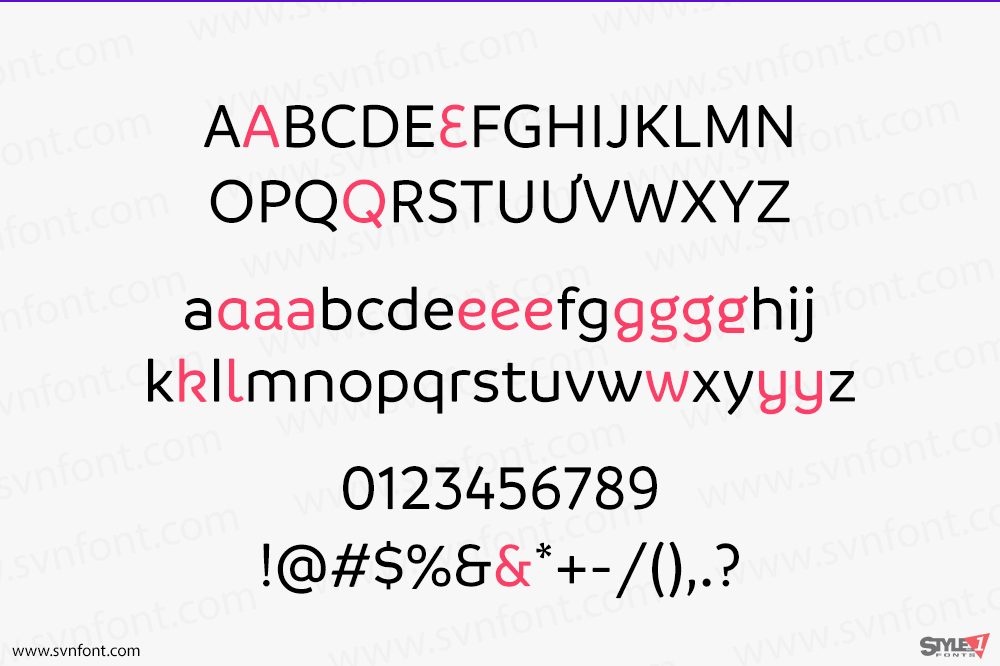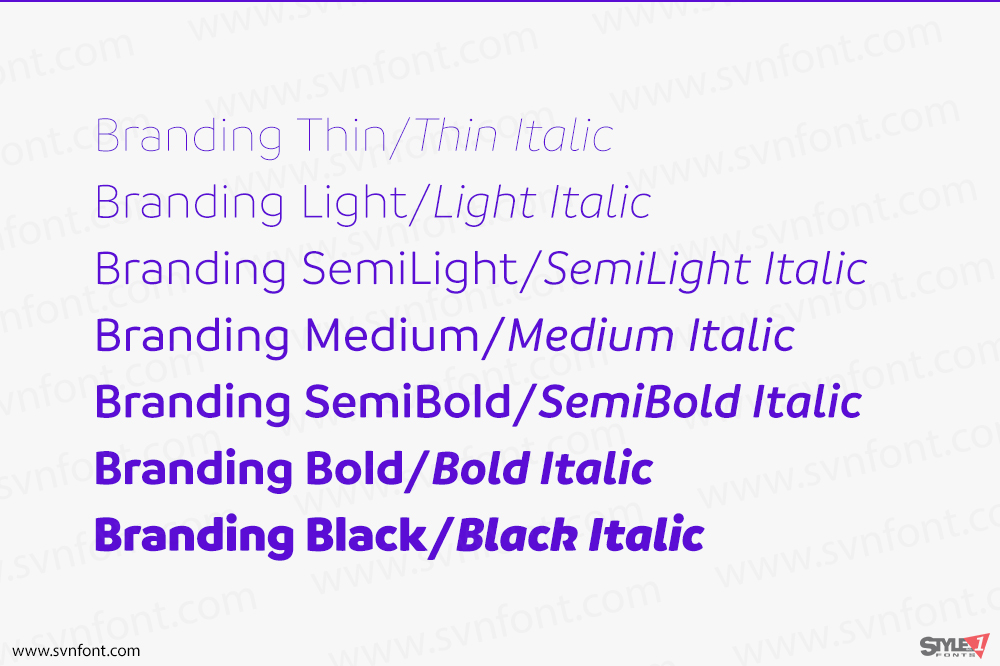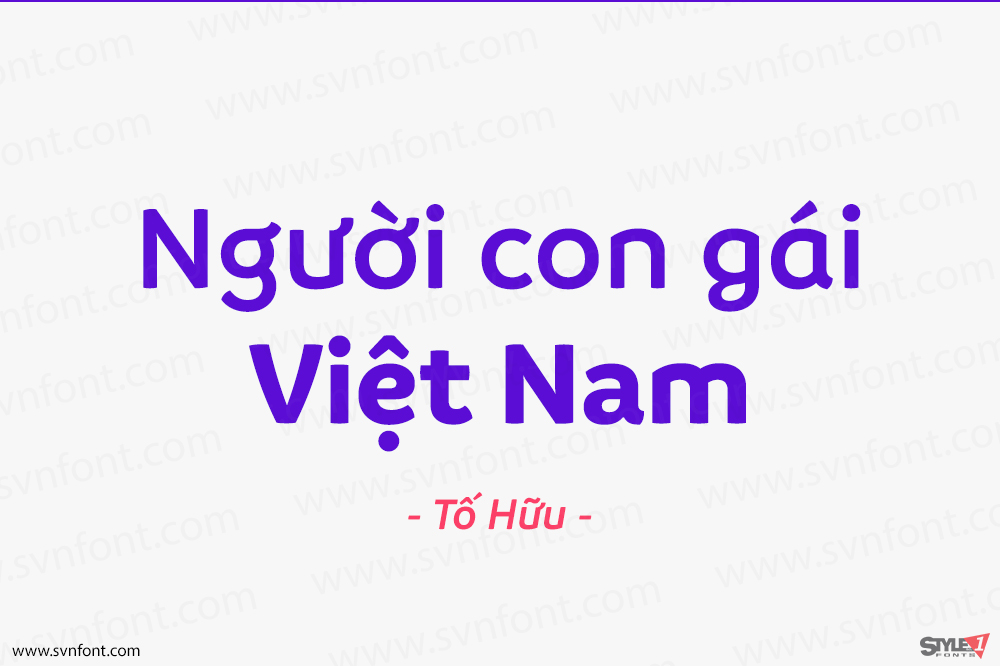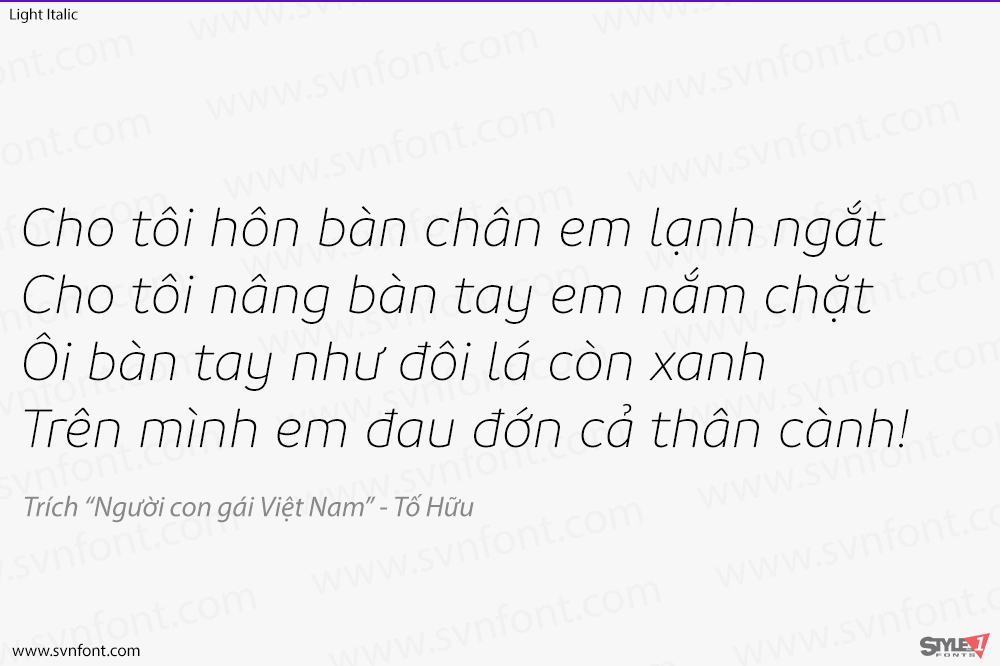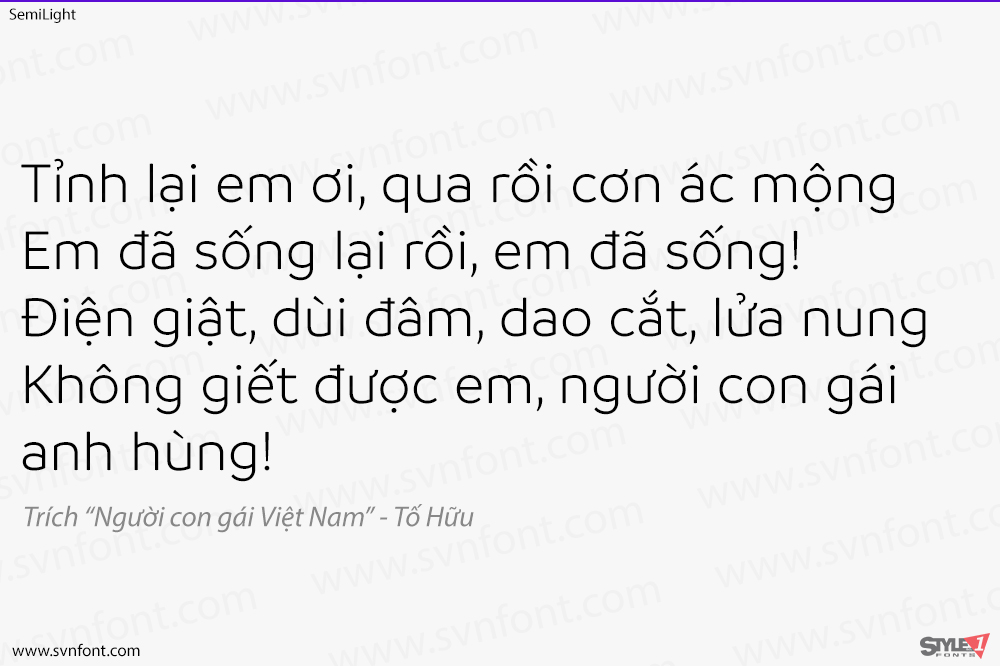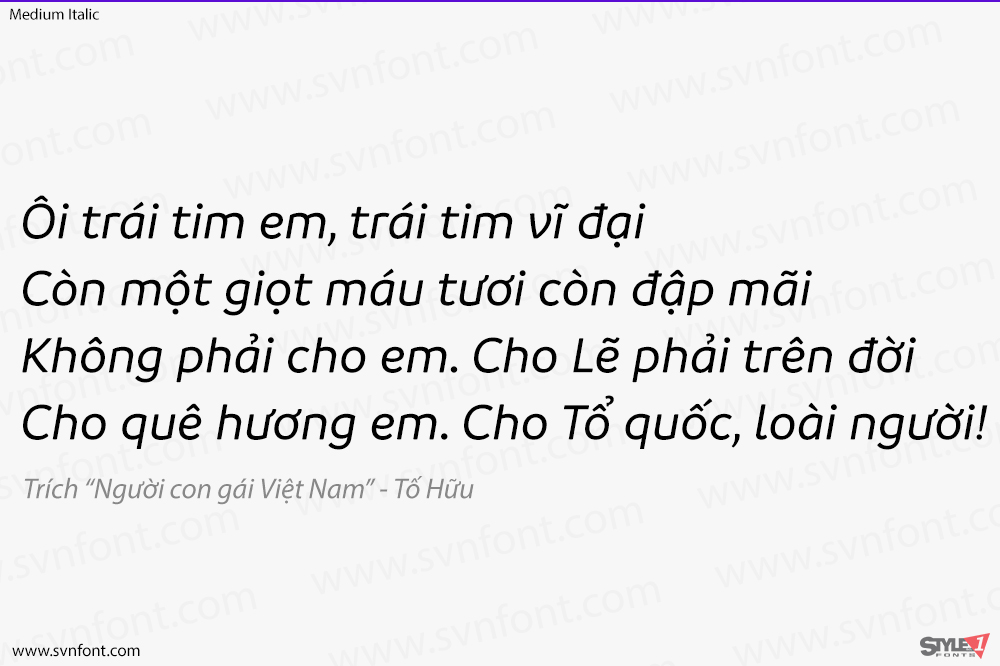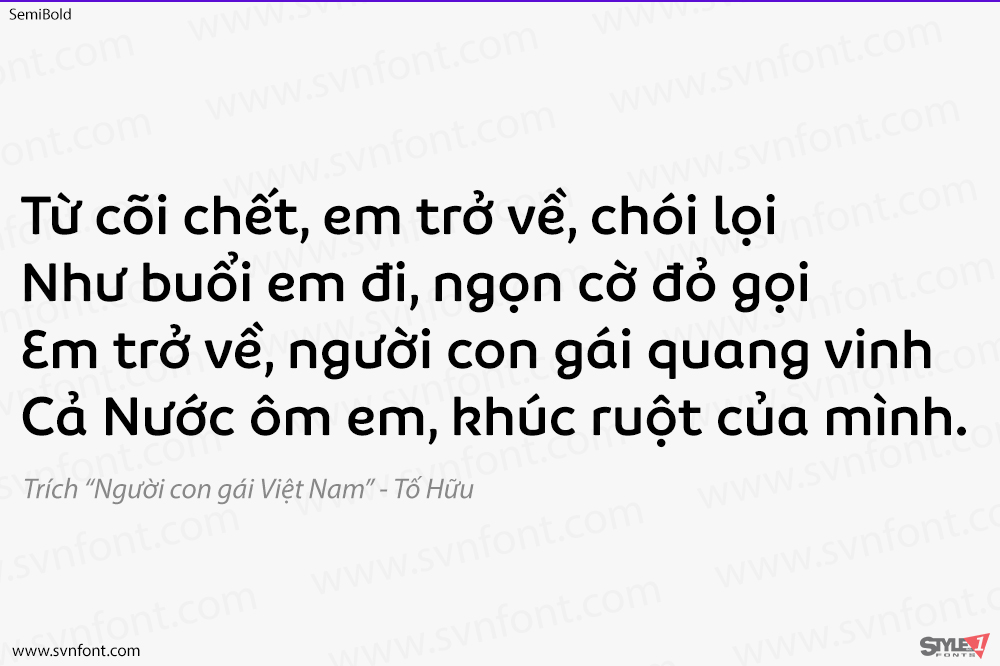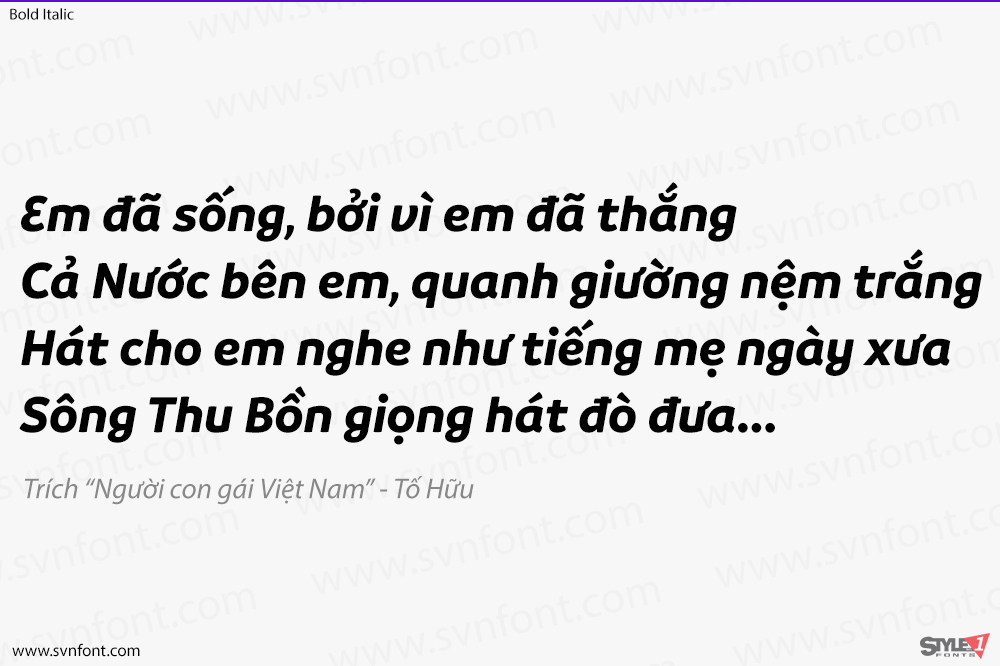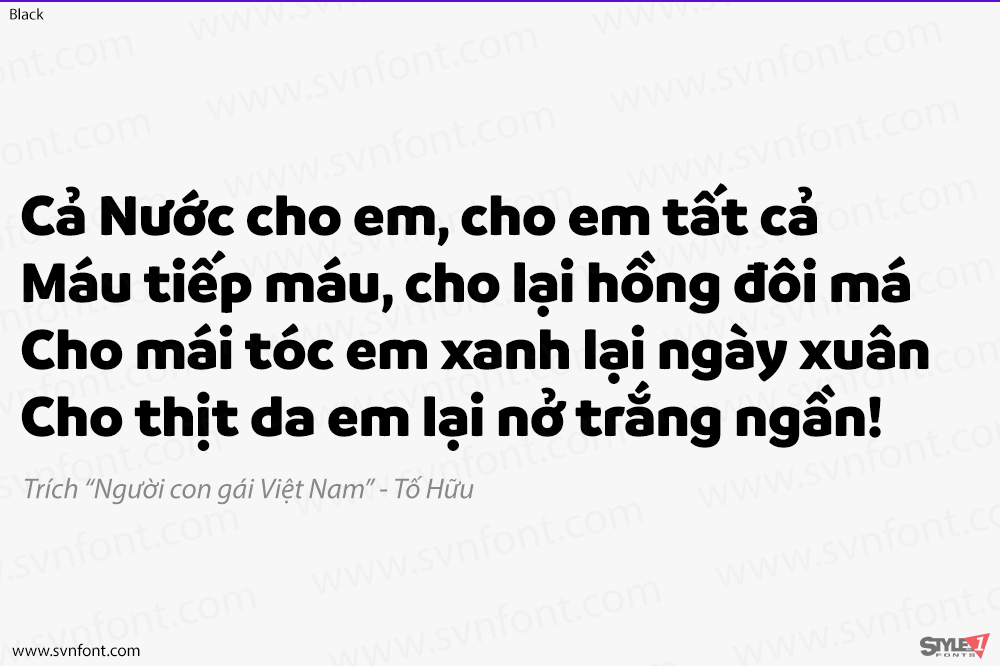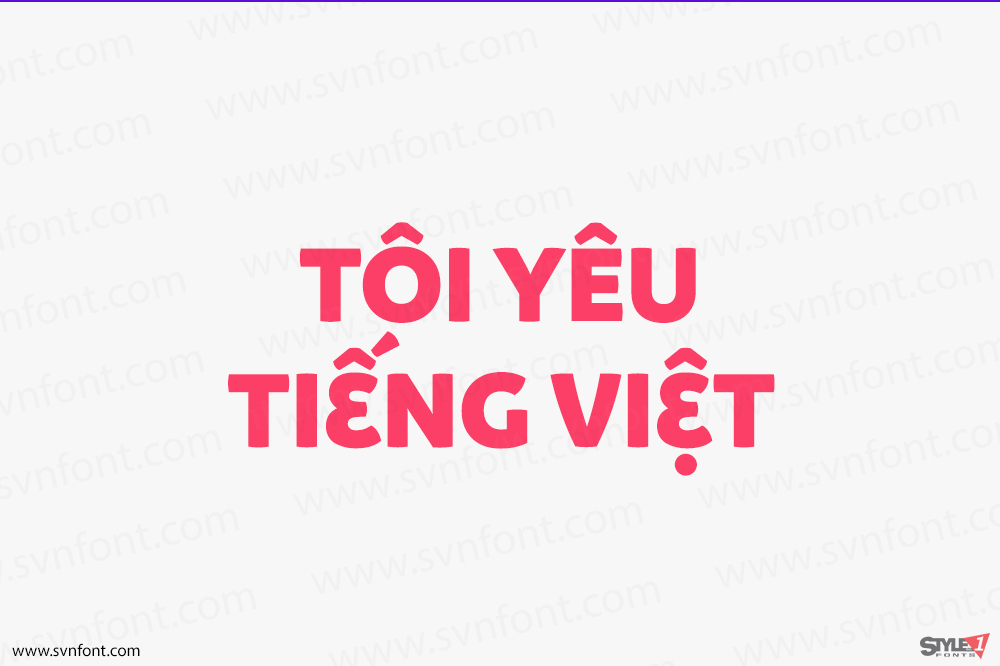
Branding, một kiểu chữ hiện đại cho những nhu cầu hiện đại! Branding, được thiết kế đặc biệt để đáp ứng các nhu cầu thẩm mỹ và chức năng đương đại, là sự diễn giải về một kiểu chữ hiện đại từ góc nhìn của nhà thiết kế. Kiểu chữ này bao hàm một loạt các sắc thái và kết hợp những yếu tố có vẻ đối lập như công nghệ và các hình dạng bo tròn thân thiện. Ngoài ra, các ký tự thay thế khiến Branding trở thành một công cụ lý tưởng cho cả nhà thiết kế đồ họa và giám đốc nghệ thuật. Branding là một kiểu chữ sans-serif không chân với chiều cao x trung bình lớn, tỷ lệ chiều ngang hơi rộng hơn, các đường cong thẳng và các đầu mút lồi. Phông chữ này rất phù hợp cho logo, biểu tượng, văn bản ngắn, v.v. Branding có 7 độ đậm—từ Thin đến Black—với các chữ nghiêng tương ứng và bao gồm một bộ 544 ký tự hỗ trợ 128 ngôn ngữ khác nhau. Các dấu phụ châu Âu, chữ số kiểu cũ và nhiều ký tự thay thế cũng được bao gồm.
Nhà thiết kế: Luciano Vergara, Daniel Hernández, Alfonso García, Latinotype Team
Nhà phát hành: Latinotype